フォントと組版の本
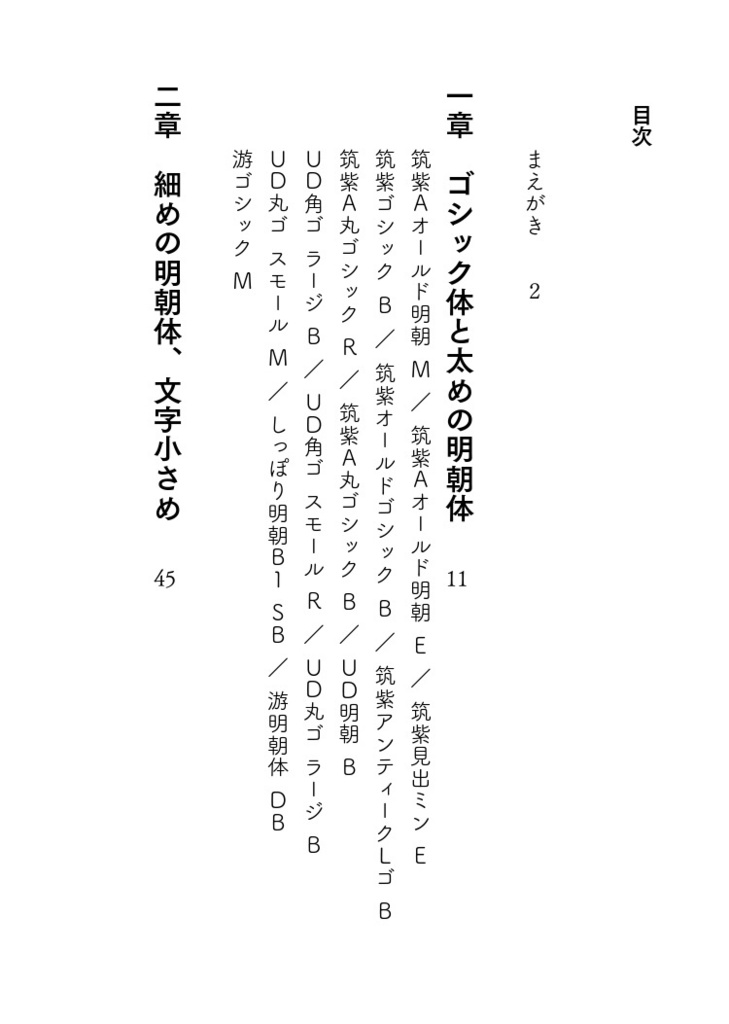
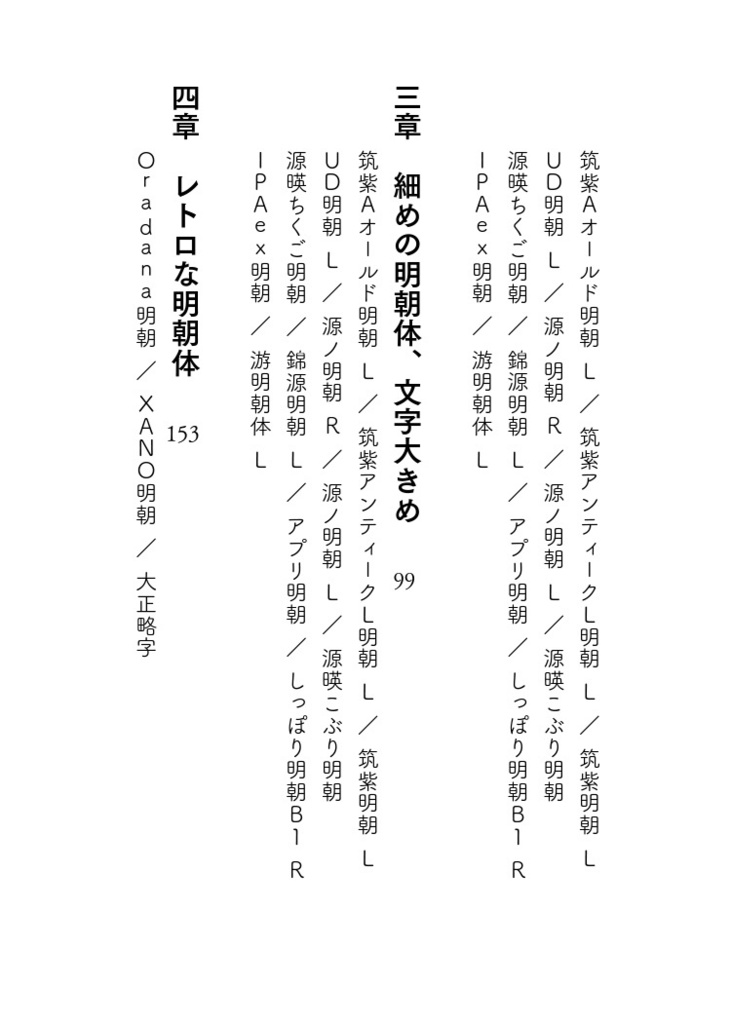
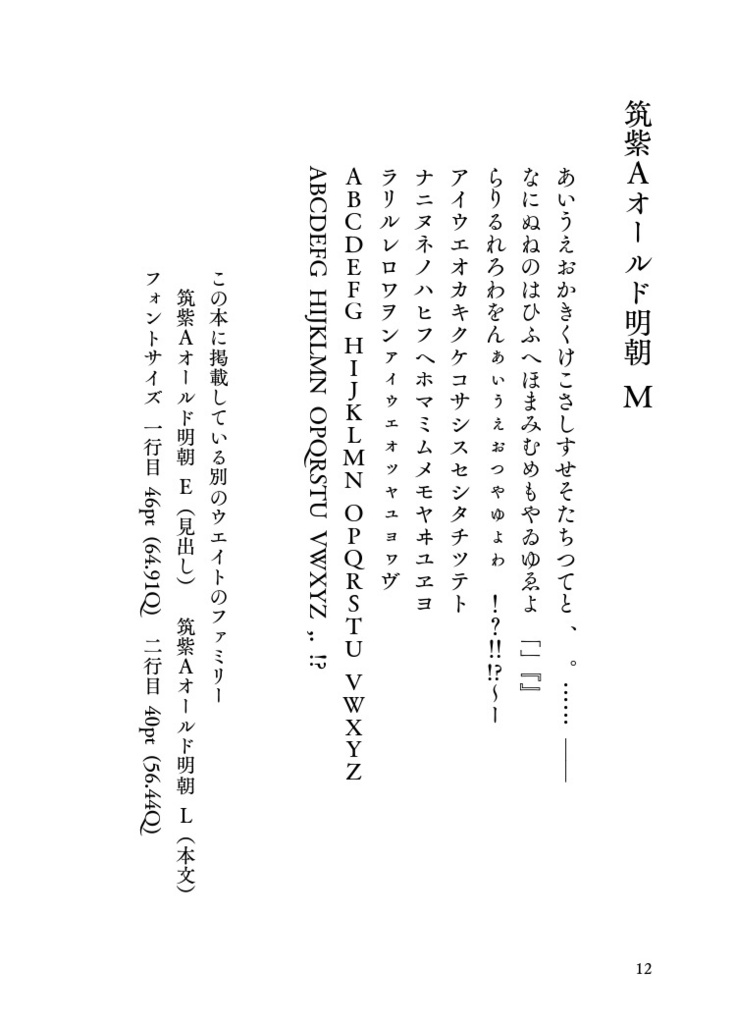
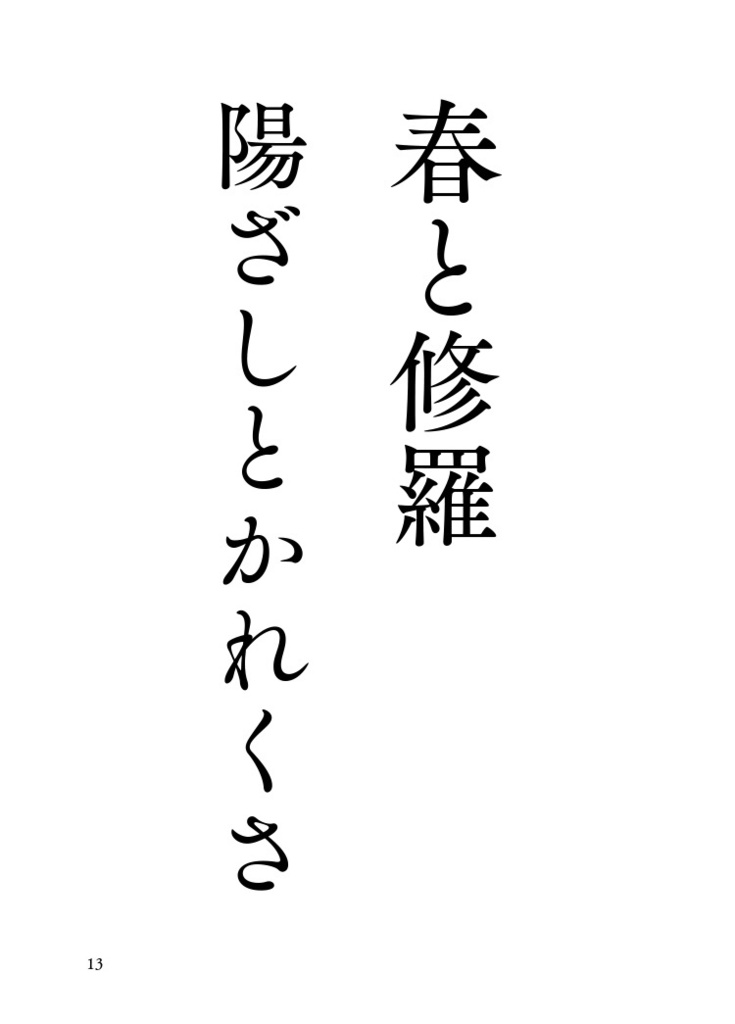
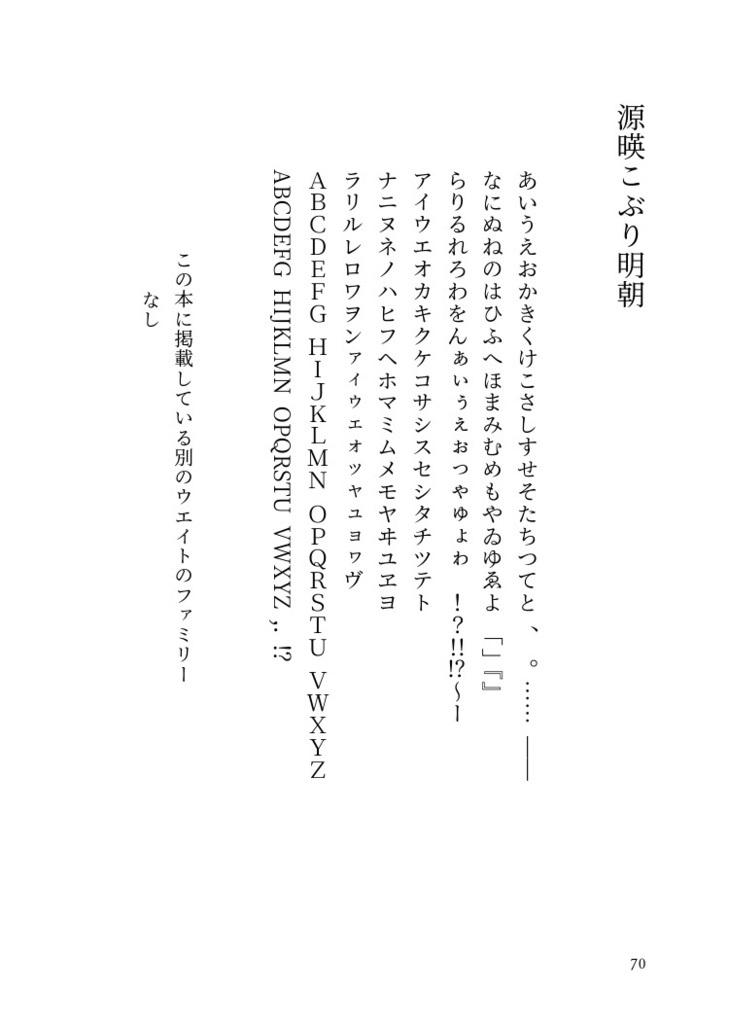
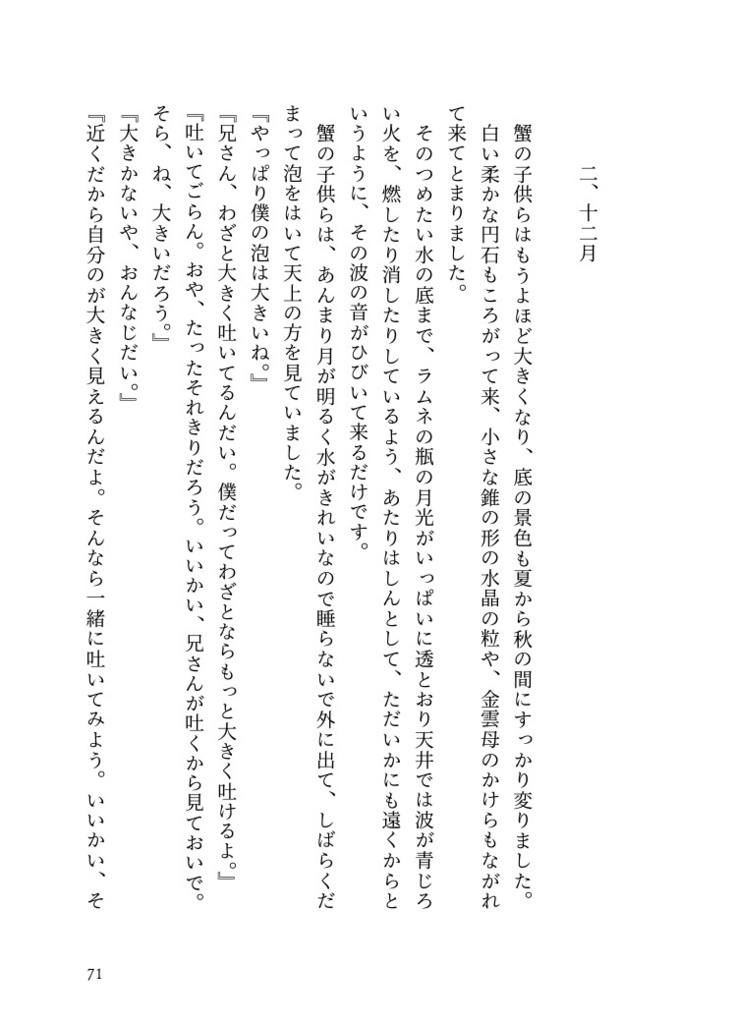
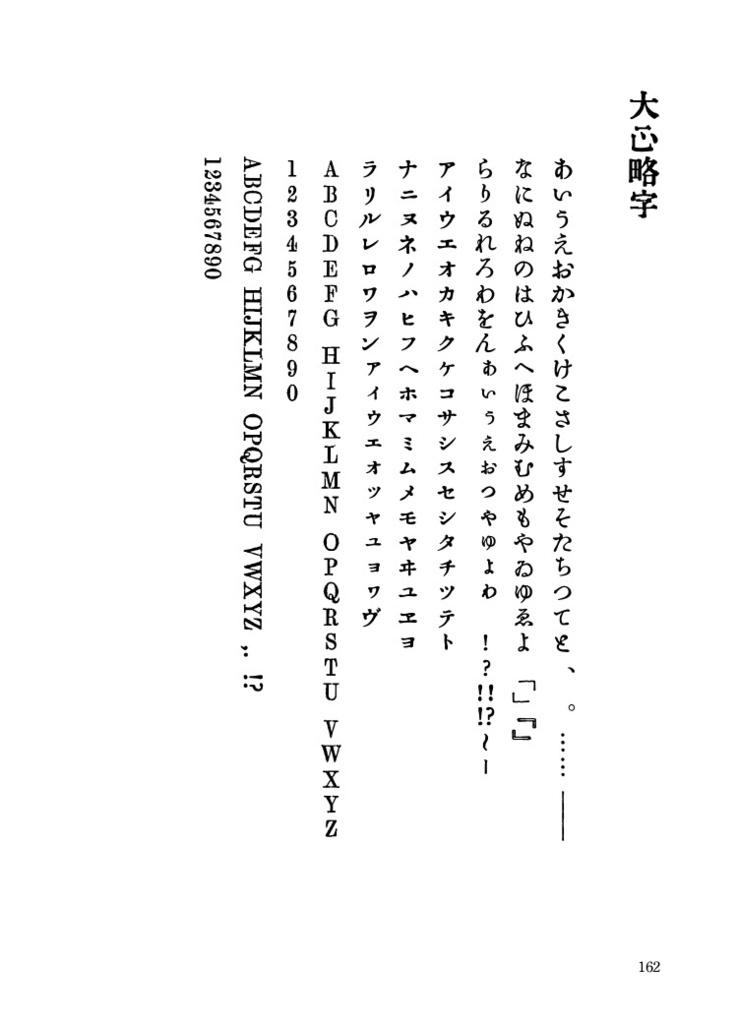
フォントと組版を色々試してみる本を作りました。 A6(文庫サイズ)、168ページ ------------------------- 私、筑紫フォントに一目惚れしました。 一太郎プラチナ2021についていた筑紫フォントを眺めているうちに、このフォントたちを小説の本文で使うとどんな雰囲気になるのか試してみたくてたまらなくなりました。 それで作ったのがこの本です。 手持ちの筑紫フォントだけでなく、プリインストールのフォント、フリーフォントも使用ししました。25種類(ウエイト違いをカウントすると32種類)のフォントで、本文を組んだり見出しを作ったりしてみました。 なにぶん、素人の本ですので、至らない点が多数あるかと思います。ご意見などありましたら頂戴したく存じます。 小説同人誌を作成される方、フォントがお好きな方、組版の雰囲気の違いを感じてみたい方。よかったらお手に取って頂けると幸いです。 (おまけ) この本の仕様(各種設定、使用した紙の種類など)にご興味おありの方は、購入後、ご連絡ください。可能な限りお伝えしたいと思っています。あなたの本作りの一助になればこんなに嬉しいことはありません。